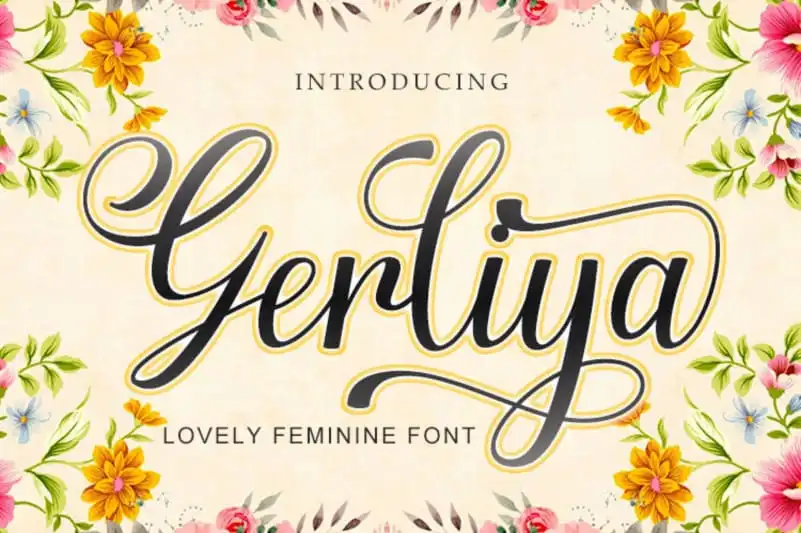
Gerliya Calligraphy Font – Download Grátis
A Gerliya Calligraphy Font é uma deliciosa tipografia script com atmosfera contemporânea e perfeição de forma, inspirada por uma chamada clássica eterna que se mantém fresca para os tempos atuais. Com um traço adequado, esta fonte não é sólida nem fina demais; ela é equilibrada e variada, projetada para tornar seus projetos mais belos ainda. Essa fonte traz beleza e elegância a qualquer projeto onde for usada, seja em cartões de agradecimento, selinhos de vídeo ou até mesmo em elementos gráficos decorativos. Atrairia aqueles que buscam uma fonte de chamada que transmite elegância clássica num formato moderno e versátil. Com certeza, será um excelente complemento para quem procura uma fonte chamativa e única para seus projetos de design.